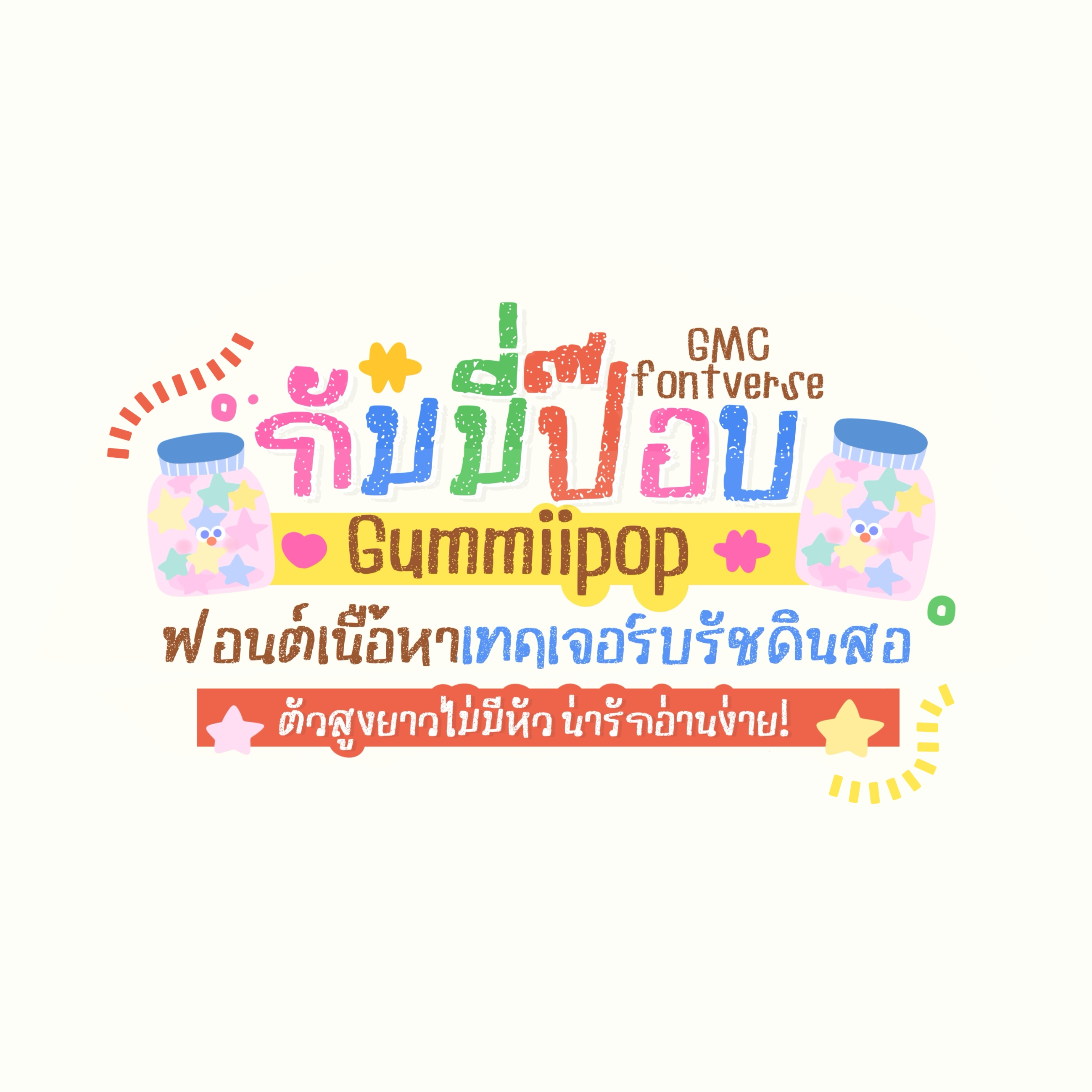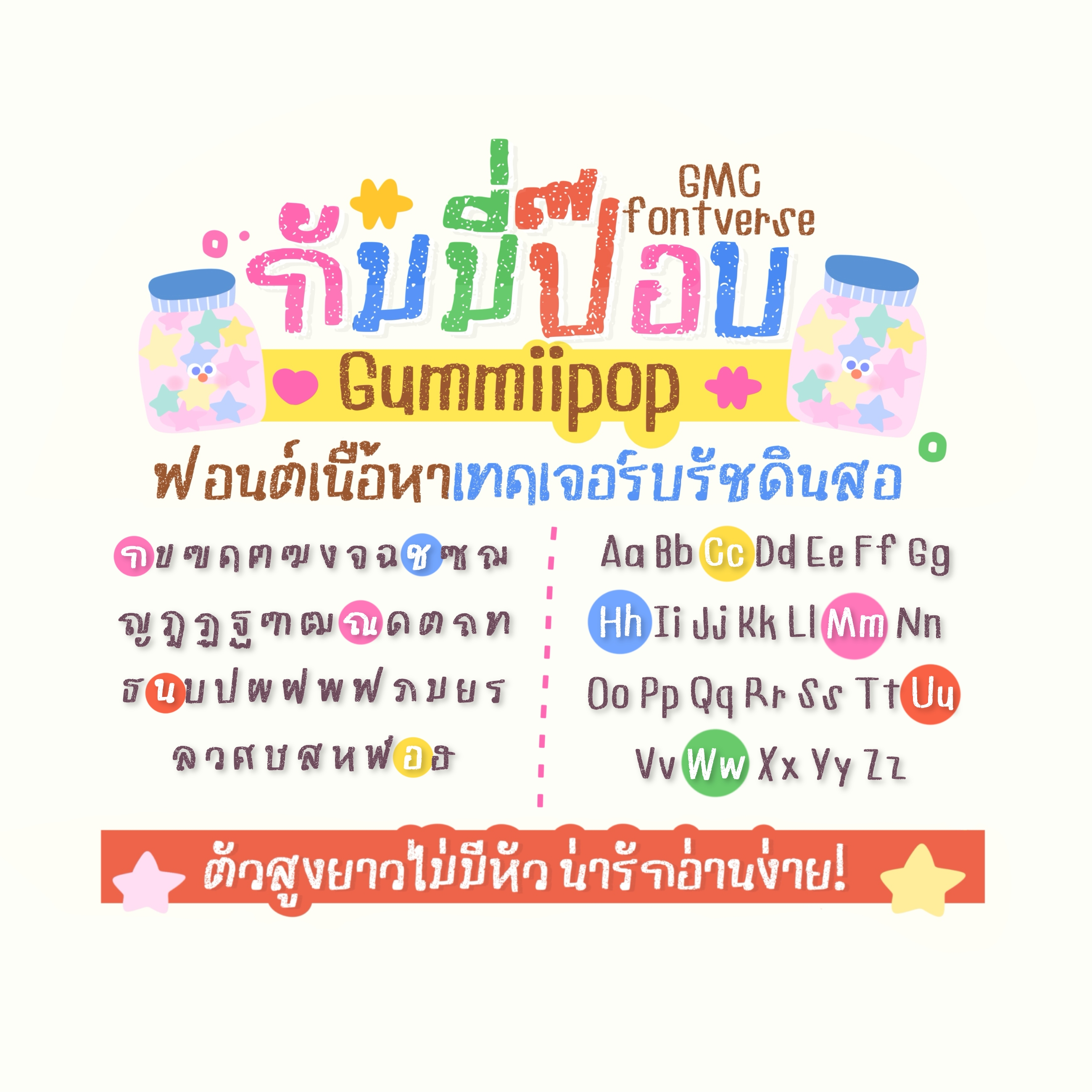
ชื่อฟอนต์ : กัมมี่ป๊อบ (GMCfnGummiipop)
ไฟล์แจกฟรีเป็นแบบทดลองใช้เท่านั้น ตัวอักษรมีความไม่เท่ากัน มีตัวหนา ตัวโปร่ง
ไฟล์เต็มมี 1 ขนาด เป็นบรัชสไตล์ดินสอ